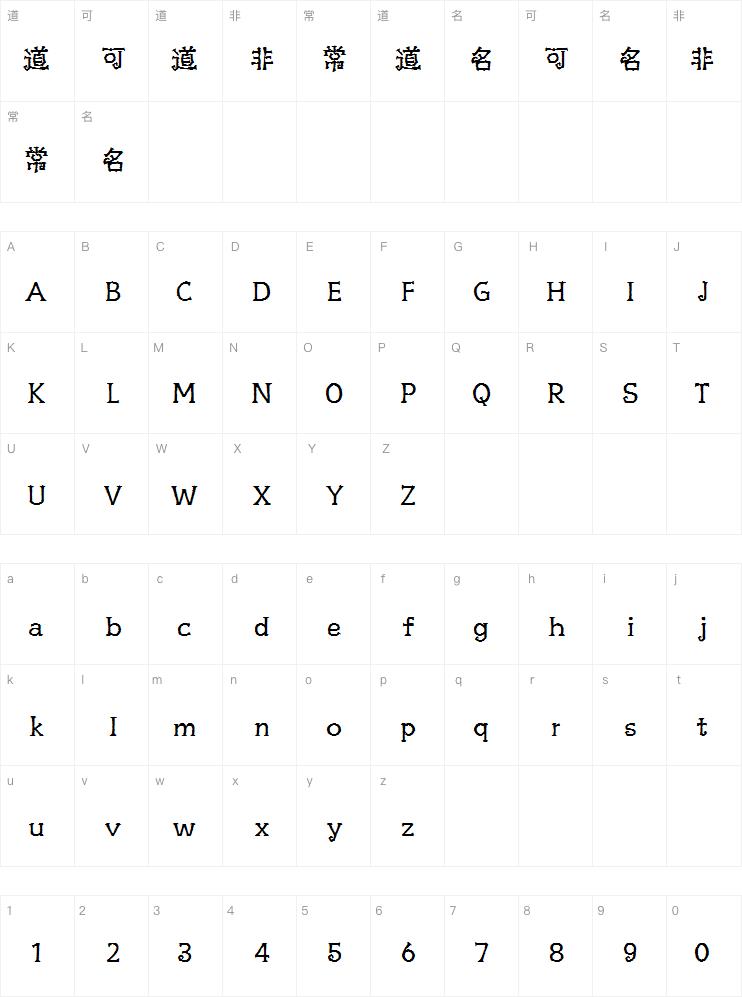
山海暗黑森林,是一款全新的字体,包含汉字9169个,符号200+个。该字体是一款卡通手绘风哥特字体,该字体融合了西方哥特元素,字体独特,新颖华丽。这款字体有着很强的装饰性和醒目的视觉效果,字体重心略微偏上、结构空间均衡、字面趋于瘦高长方形,整体感觉稳重规整。字形灵动多变,童趣可爱,同时融入荆棘刺型结尾,装饰性十足,带给人魔幻、华丽的视觉感受。撇和捺作为字形中延展性最高的两个笔画,形态华丽灵动。在制作过程中融入卡通的手写方式,枯笔形成游丝飞白,从而使得该字体字形灵动多变,在灵动的同时而又极富俏皮感。在粗细的纵横间,拥有非常规的自由灵动特性。笔画的飞白效果使字体的气息更加流畅,笔画间的关系密不可分,同时也增加了字体的自由洒脱之感。整体造型生动有趣,具有灵活的适用性,天真俏皮又不失时尚感。在体现哥特风格的同时呼应了中文的笔画特征,并在设计上有意改善传统哥特体复杂难辨认的特性,尽量做到易辩、易读,保证了字体的实用性。汉字艺术与西方文字的融合,如精灵国度般华丽高贵,又宛如梵高的《星月夜》般神秘梦幻;个性鲜明的字体特征,散发着神秘而华丽的气息。在华丽而不失婉约中,感受哥特风的魅力。